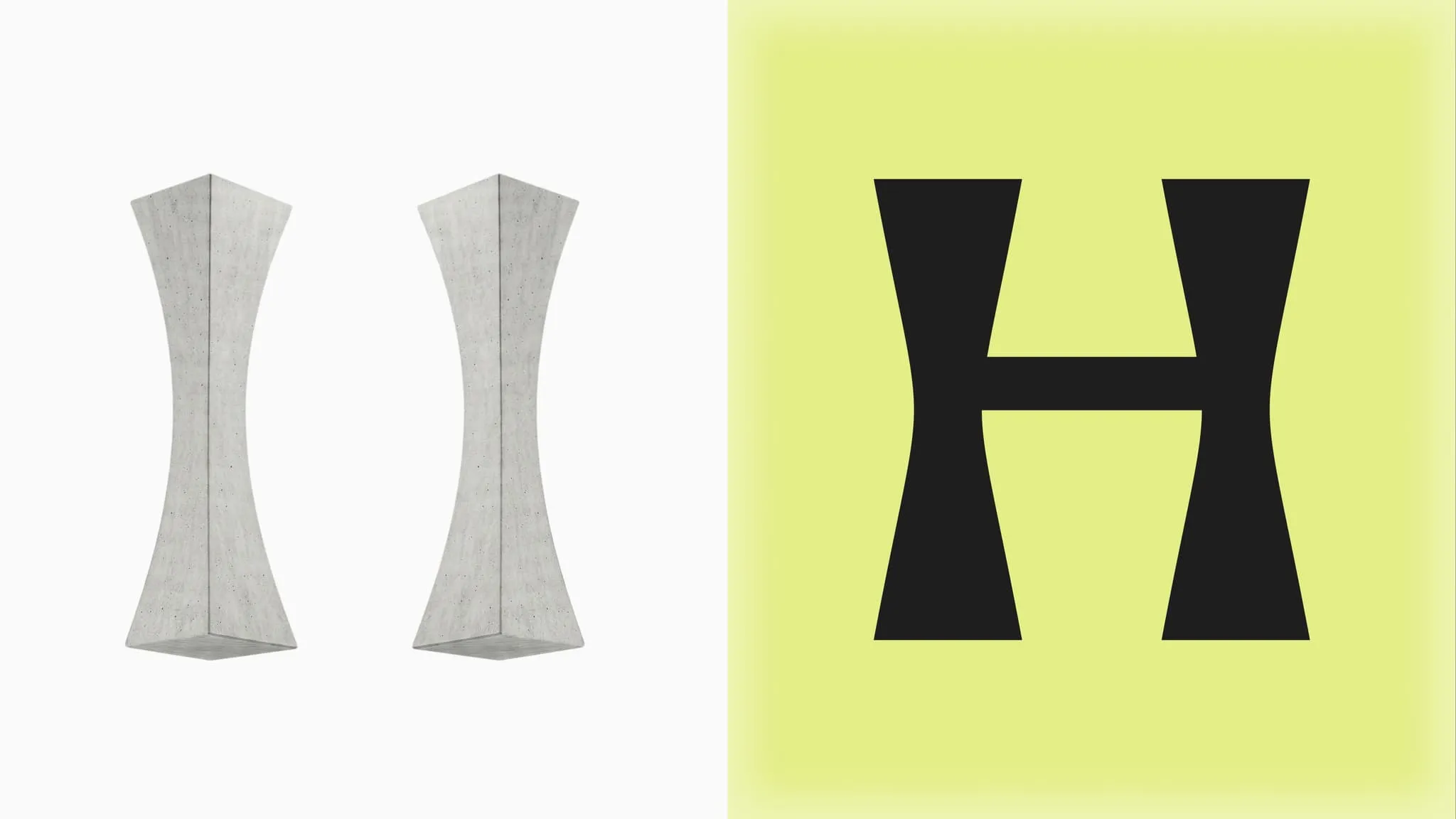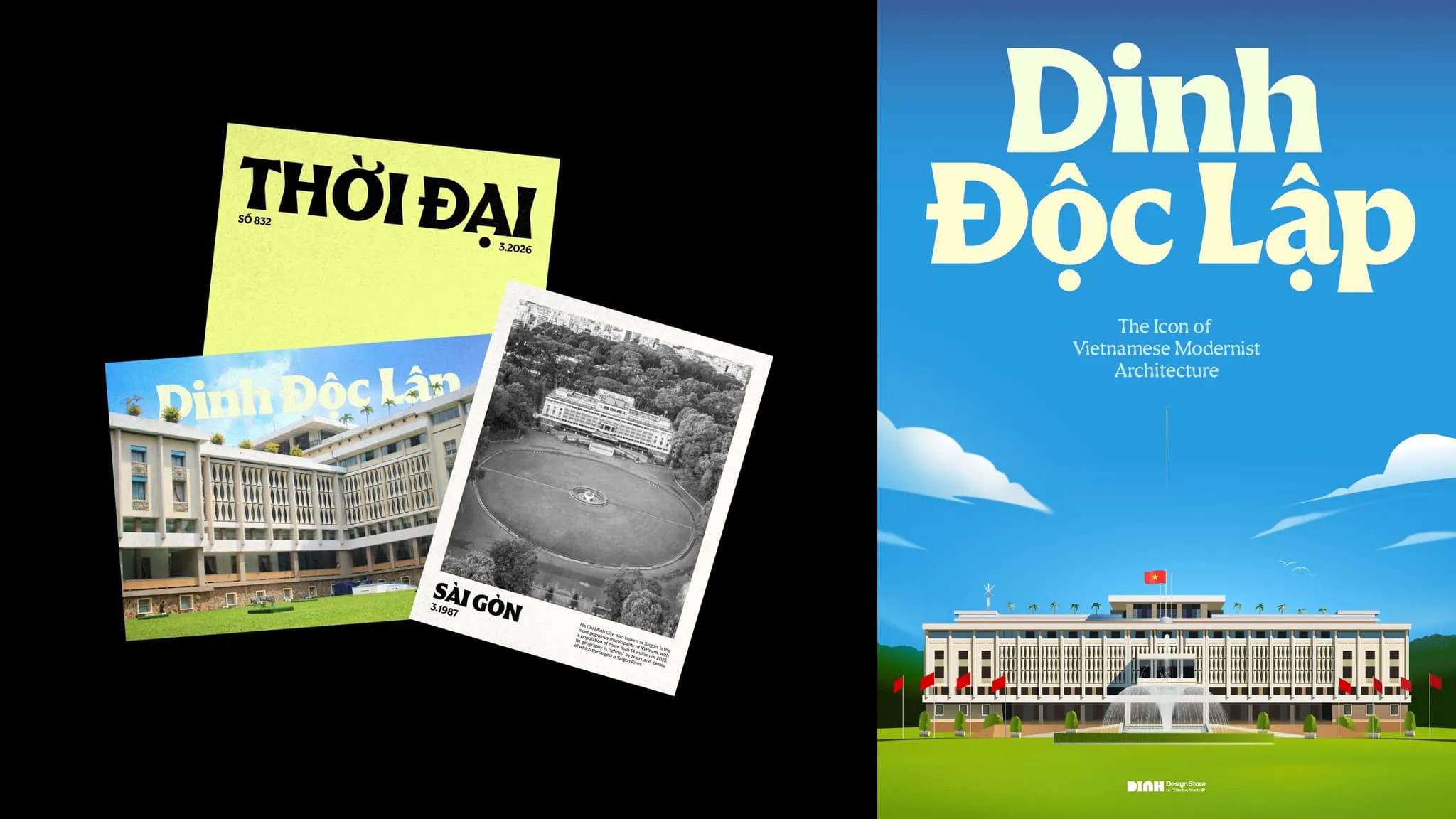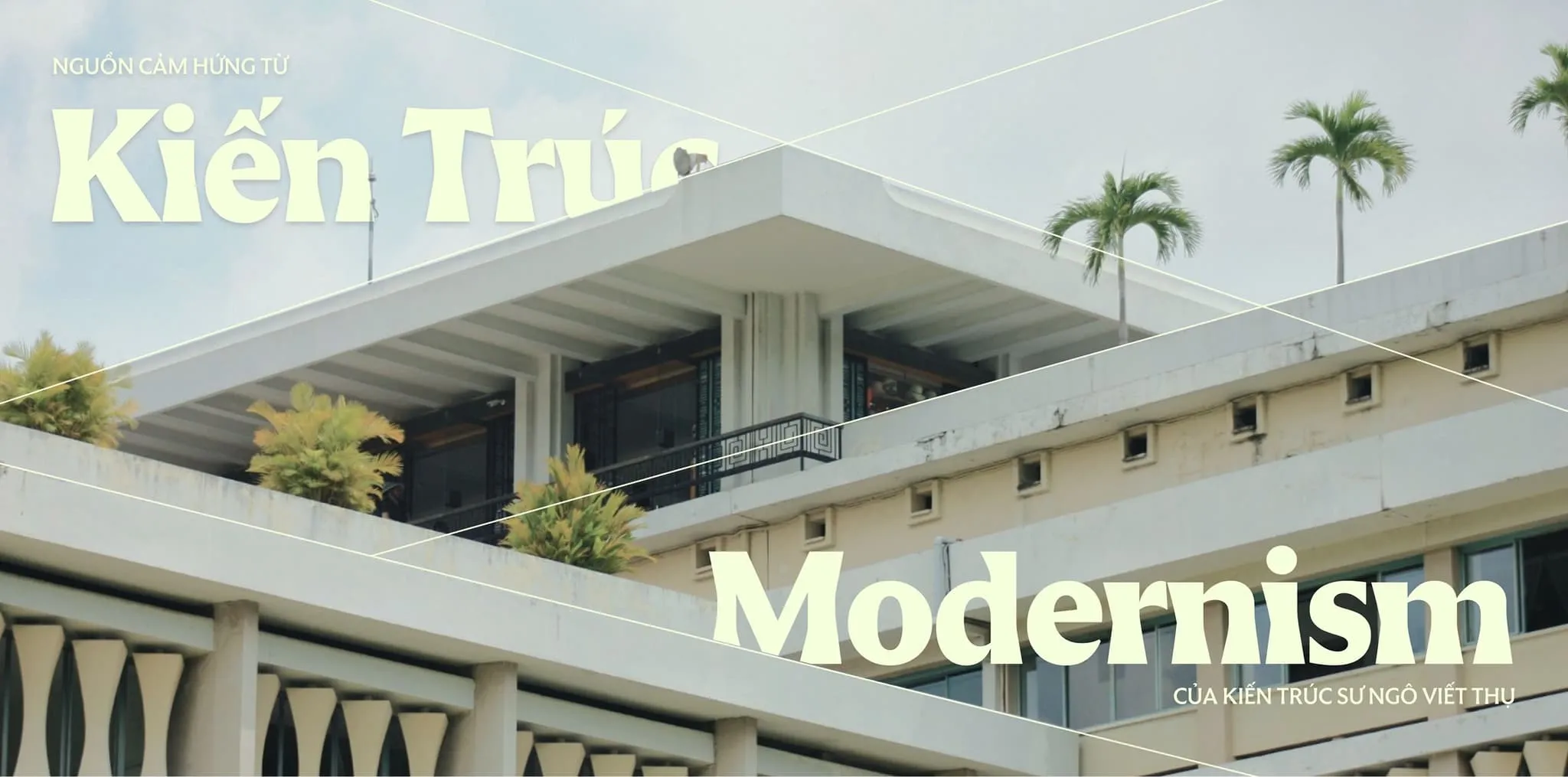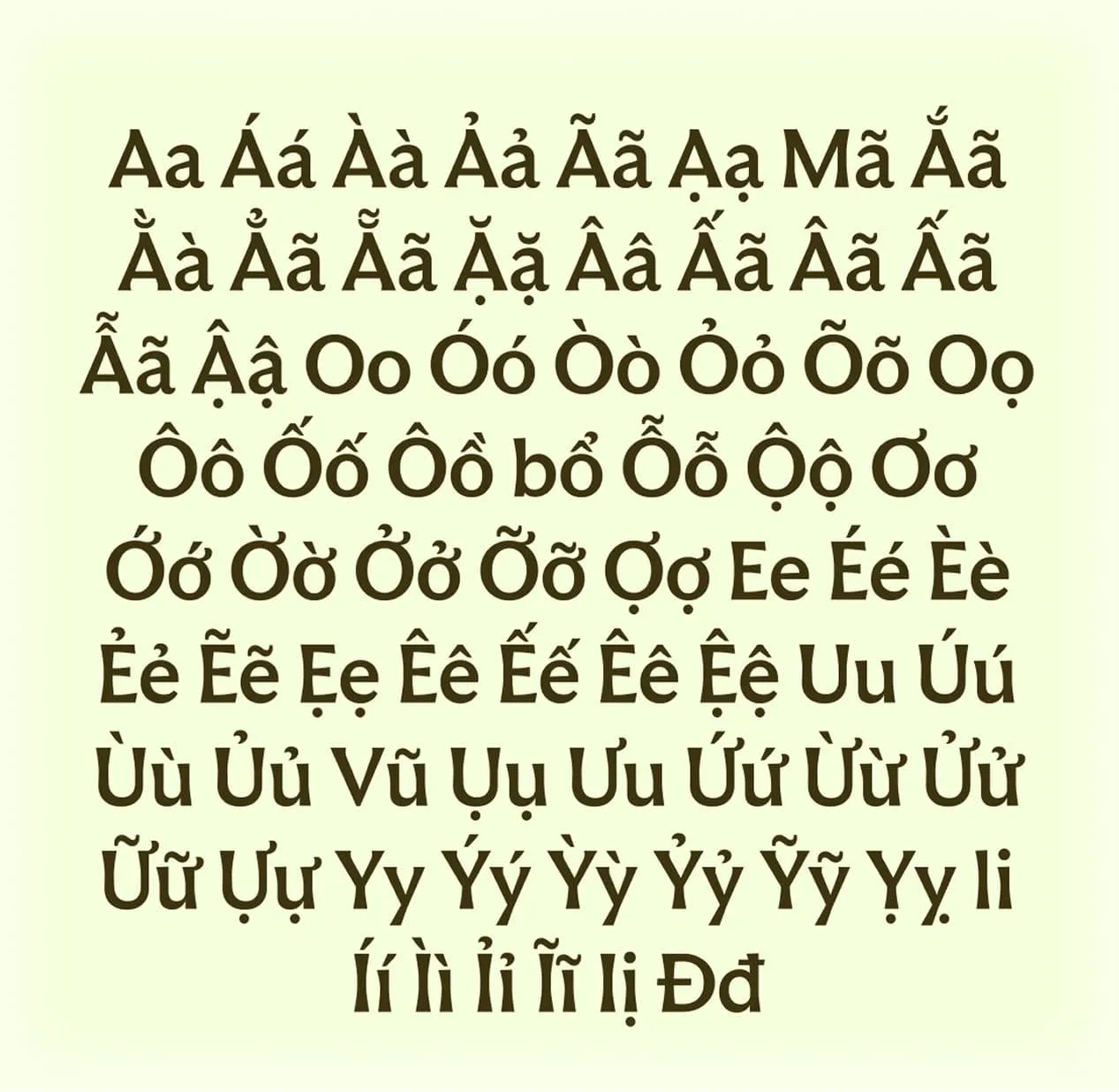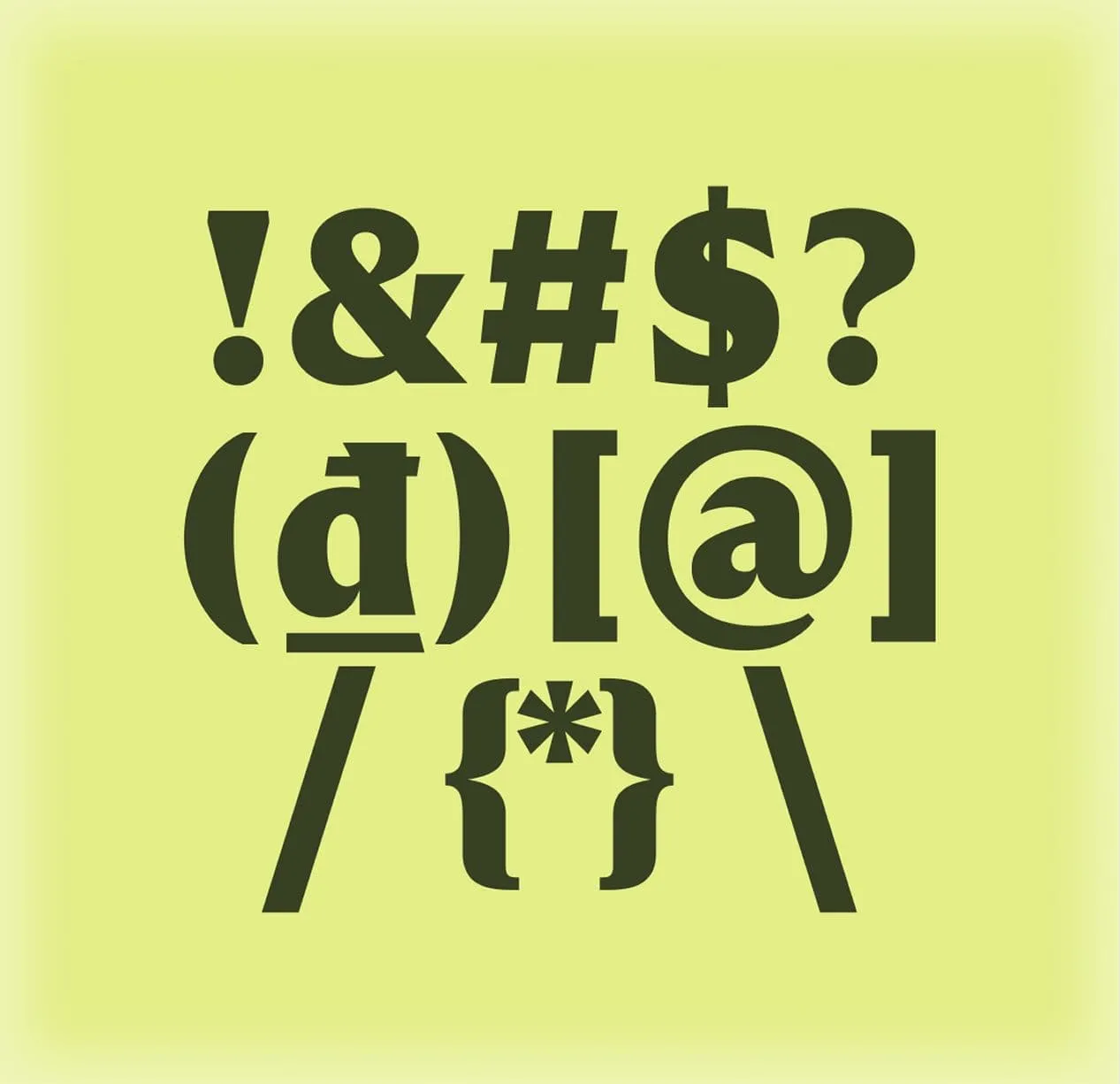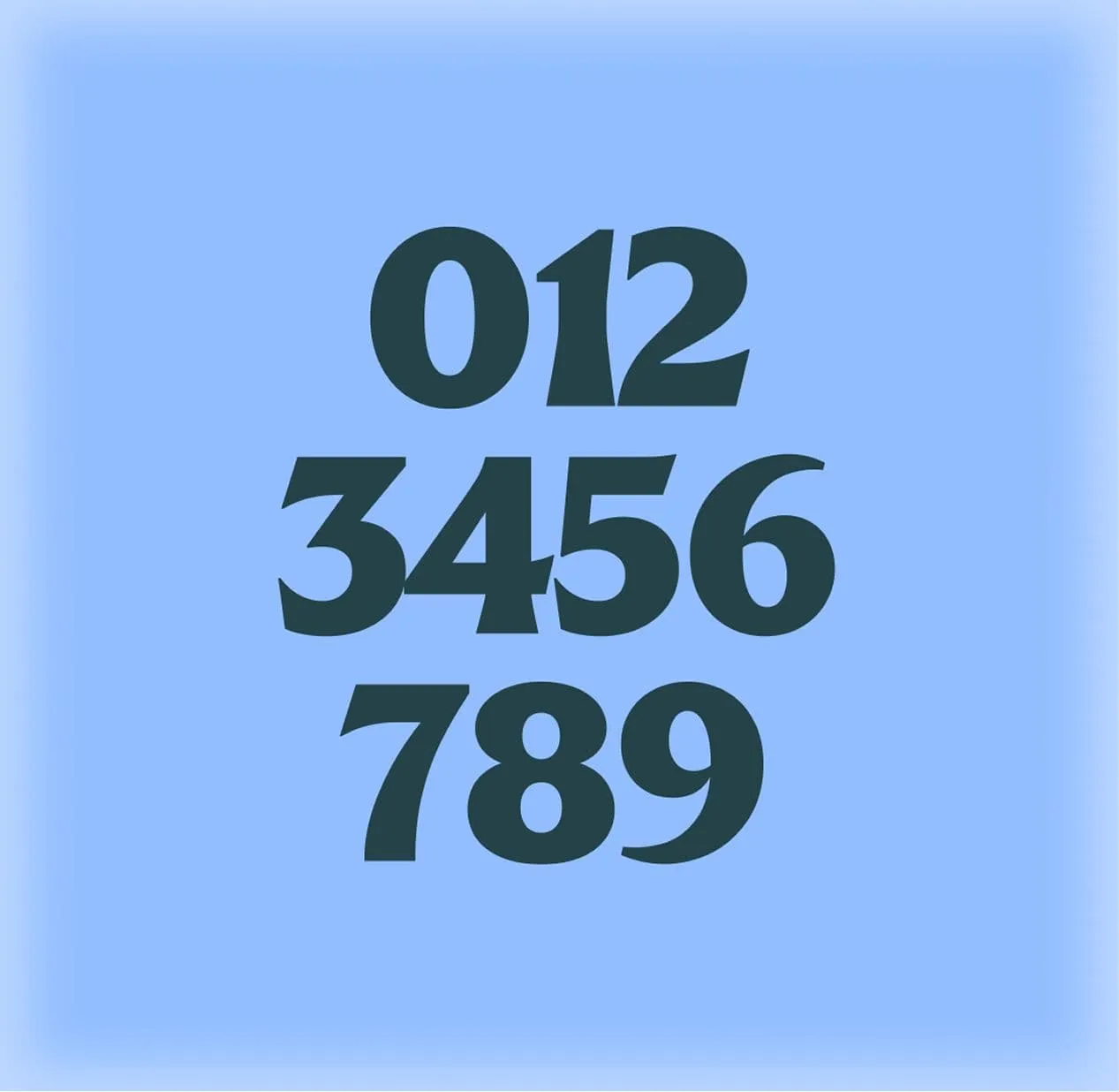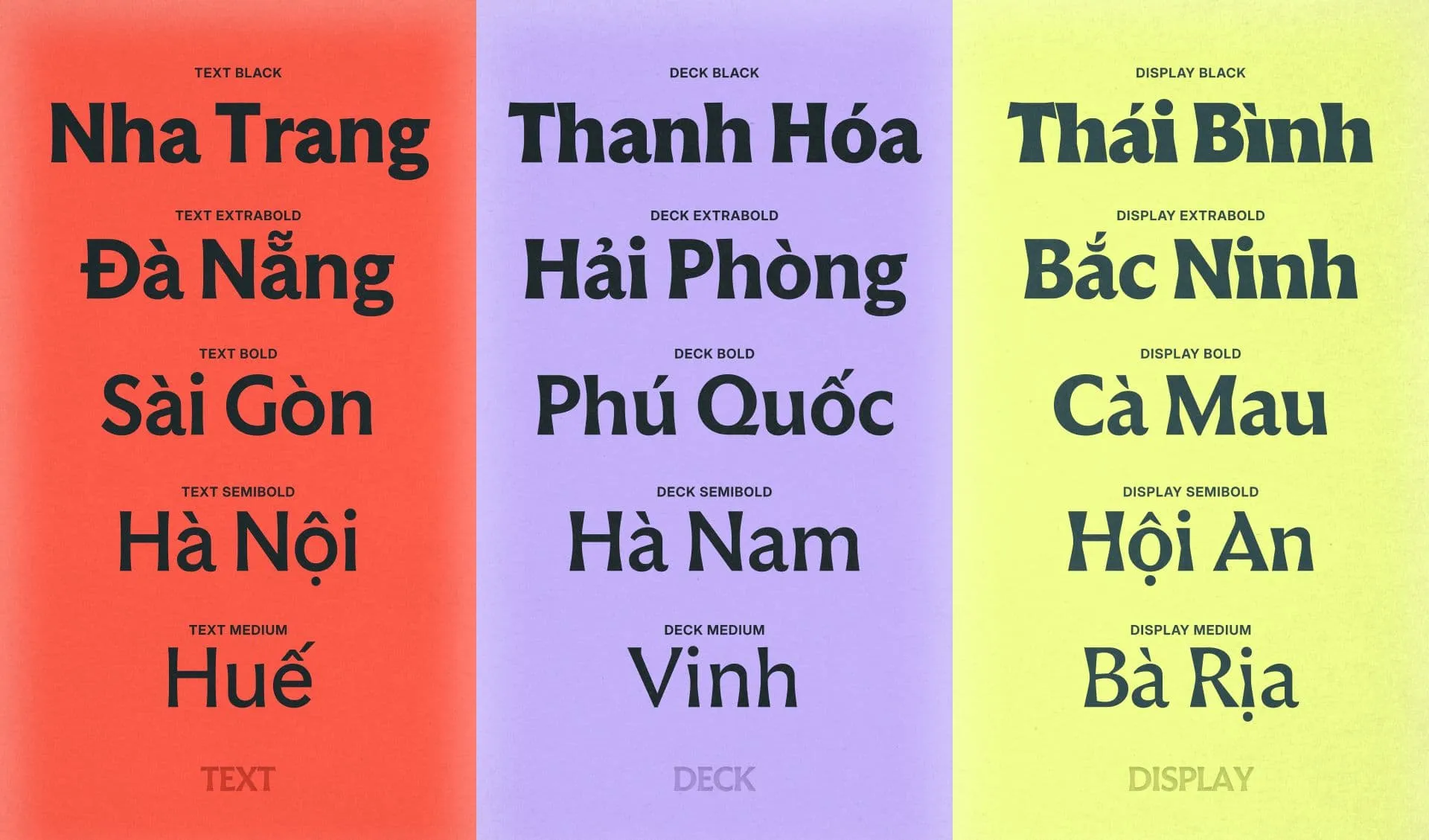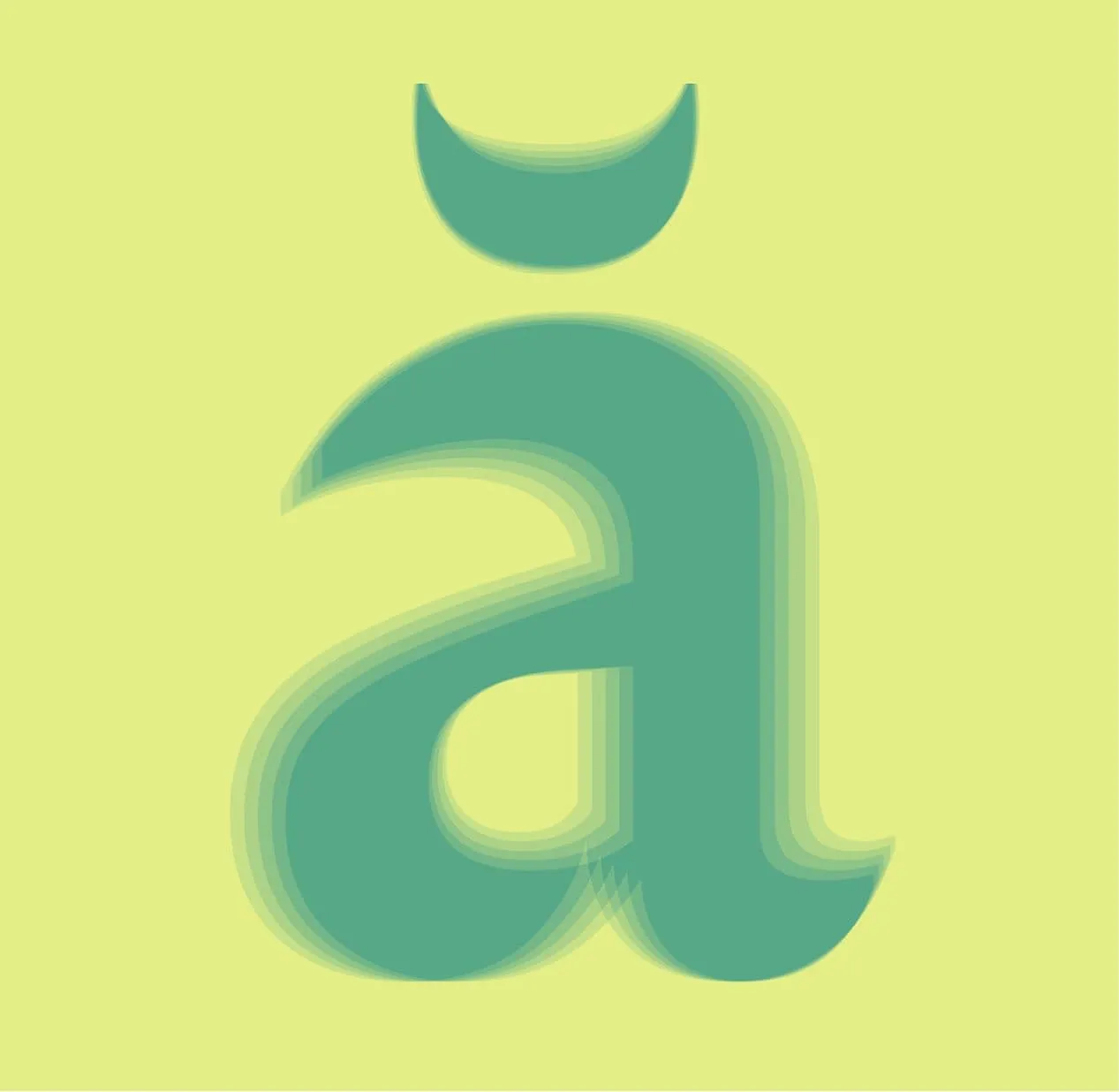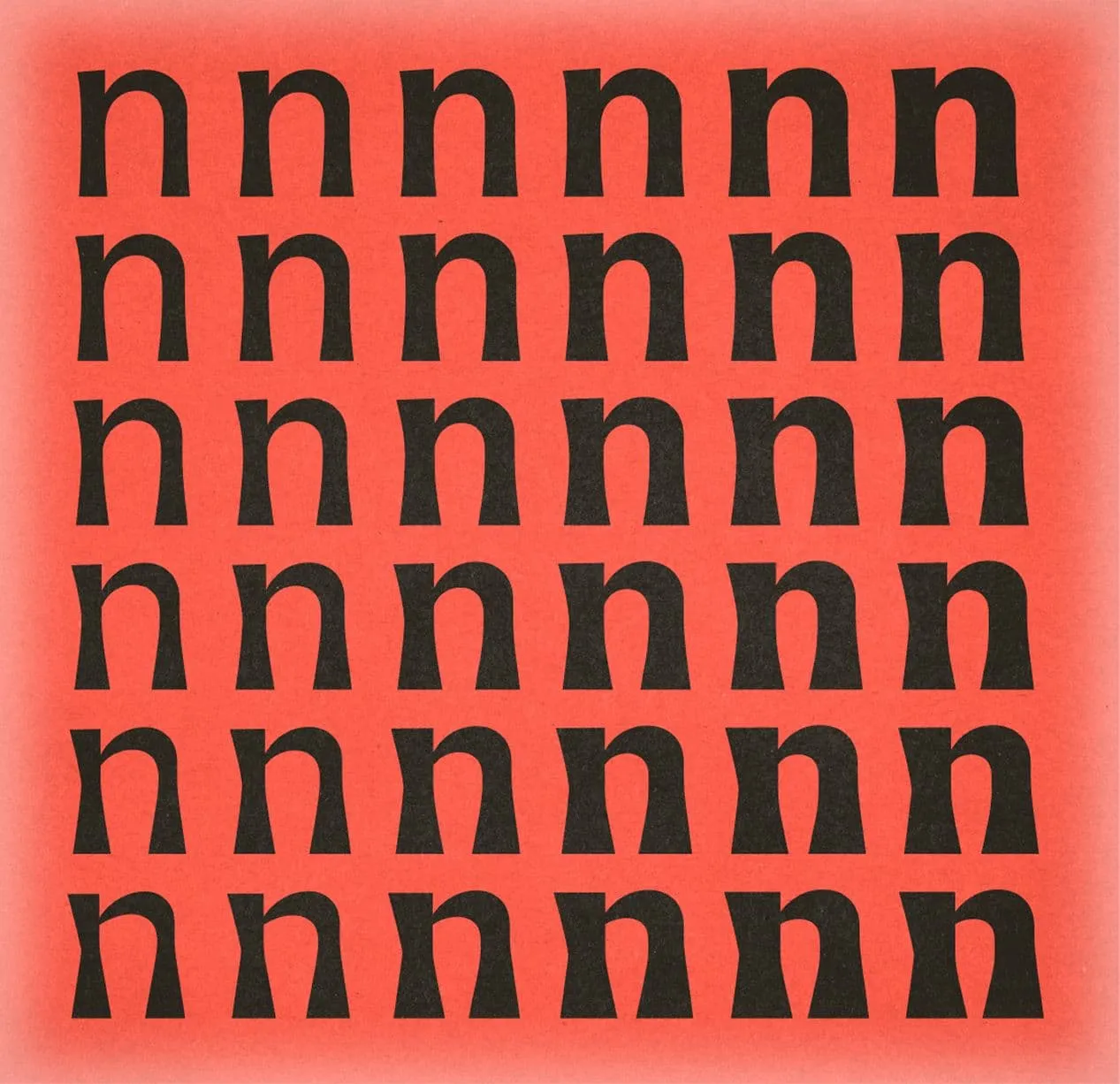
CDA Independence: A Variable Typeface Inspired by the Independence Palace’s Stone Lattice CDA Independence is a versatile variable typeface created by Cōllective Design Agency (CDA) in collaboration with the Independence Palace. The project transforms iconic concrete stone lattice motifs into a fresh, modern visual language.
Inspired by Architectural Rhythm The creative spark behind the font comes from the brise-soleil (stone lattice screens) surrounding the second floor of the Independence Palace—an architectural landmark designed by Ngô Viết Thụ. The CDA design team translated those architectural elements into typography through rhythmic repetition, layering, contrast, and subtle elegance.
Design Details & Vietnamese Diacritics Each character in CDA Independence carries structural cues from the stone lattice pattern. The contrast, serifs, and terminals are carefully calibrated for punchy clarity and smooth flow. Right from the start, Vietnamese diacritics were built as a foundational part of the type design, optimizing spacing for everything from large display headers to short body copy.
2-Axis Variable Design Crafted as a variable font, it offers two custom axes: Weight and Serif. This setup lets the typeface shift seamlessly across different contexts—from clean, highly readable text to bold, expressive headlines.
Integrated Iconography As part of the broader visual identity research for the Independence Palace, a matching wayfinding icon system was developed alongside the font. The icons share the same stroke proportions and architectural shapes, blending signage and typography into one cohesive design system.
CDA Independence: Bộ font chữ biến thể lấy cảm hứng từ rèm hoa đá Dinh Độc Lập
CDA Independence là bộ font chữ biến thể (variable typeface) do Cōllective Design Agency (CDA) thực hiện qua sự hợp tác cùng Dinh Độc Lập. Dự án mang những đường nét kiến trúc bê tông đá quen thuộc chuyển hóa thành một ngôn ngữ thị giác hiện đại.
Cảm hứng từ nhịp điệu kiến trúc
Điểm tựa sáng tạo của bộ font bắt nguồn từ hệ thống “rèm hoa đá” (brise-soleil) bao quanh khu vực tầng hai của Dinh Độc Lập — công trình mang dấu ấn của kiến trúc sư Ngô Viết Thụ. Nhóm thiết kế tại CDA đã dịch chuyển ngôn ngữ kiến trúc ấy sang typography thông qua nhịp điệu, sự xếp lớp, độ tương phản và nét tiết chế chừng mực.
Chi tiết thiết kế và dấu tiếng Việt
Mỗi ký tự (glyph) trong CDA Independence đều mang cấu trúc thiết kế kế thừa từ mảng rèm hoa đá. Độ tương phản, chân chữ và nét kết thúc (terminals) được tinh chỉnh để tạo độ nét và nhịp điệu rõ ràng. Ngay từ giai đoạn đầu, hệ thống dấu tiếng Việt (diacritics) đã được tính toán như một phần cốt lõi của bộ chữ, giúp tối ưu không gian hiển thị cho cả tiêu đề lớn lẫn các đoạn văn bản ngắn.
Khả năng biến đổi trên 2 trục (2-Axis Variable)
Bộ chữ được xây dựng dưới dạng variable font với 2 trục tùy chỉnh: Weight (độ dày) và Serif (chân chữ). Cấu trúc này giúp bộ font chuyển đổi linh hoạt giữa các ngữ cảnh sử dụng: từ các đoạn văn bản yêu cầu tính đọc rõ (readability) đến những tiêu đề hiển thị cần sự nổi bật.
Hệ thống biểu tượng đi kèm (Iconography)
Nằm trong dự án nghiên cứu và phát triển nhận diện thị giác cho Dinh Độc Lập, một hệ thống icon chỉ dẫn (wayfinding) cũng được thiết kế đồng bộ với bộ font. Các biểu tượng sử dụng chung tỷ lệ nét đậm – mảnh và hình khối kiến trúc, giúp phần biển hiệu chỉ dẫn và chữ viết hòa quyện thành một ngôn ngữ thống nhất.